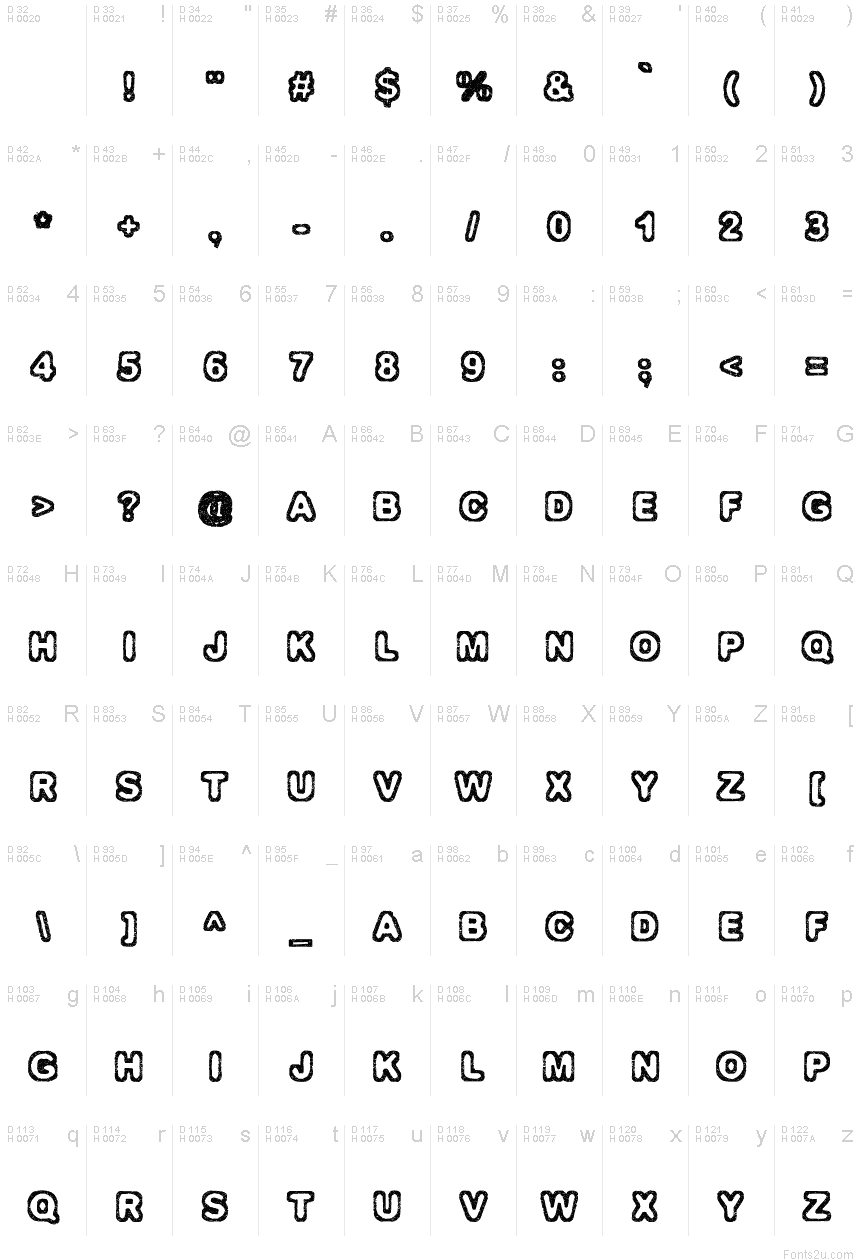
Font Izolation od SDfonts to bezpłatny, erodowany krój typu display, który zamienia masywne, „bąbelkowe” litery w coś nadgryzionego zębem czasu, podziurawionego i przetartego. Grube, zaokrąglone kontury pozostają miękkie i przyjazne, podczas gdy ziarnista tekstura wgryza się w każdy kształt niczym statyczny szum na starym ekranie, nadając każdemu słowu analogowy, surowy charakter.
Izolation natychmiast dodaje charakteru plakatom koncertowym, undergroundowym zinom, tytułom gier, grafikom streetwearowym, okładkom horrorów komediowych czy wyrazistym banerom w mediach społecznościowych. Ten darmowy font najlepiej sprawdza się w większych rozmiarach, gdzie kropkowana erozja jest w pełni widoczna. Świetnie łączy się z prostym, geometrycznym krojem bezszeryfowym w tekście głównym, dzięki czemu Twoje projekty zachowują czytelność, nie tracąc przy tym swojego surowego wyglądu.
Izolation